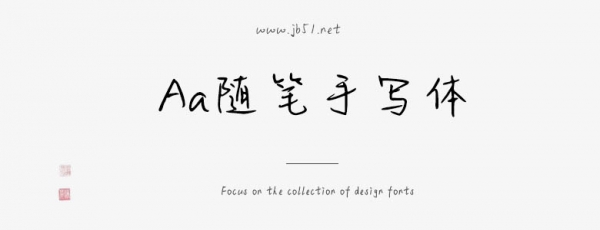
Aa隨筆手寫(xiě)體是一款不錯(cuò)的藝術(shù)字體,由Aa字庫(kù)出品,字體筆觸略細(xì),書(shū)寫(xiě)流暢,擁有字符數(shù)8040和字形數(shù)8008,具有很好的視覺(jué)感,適合應(yīng)用于藝術(shù)設(shè)計(jì)、平面宣傳設(shè)計(jì)、網(wǎng)頁(yè)設(shè)計(jì),書(shū)法字帖等領(lǐng)域,需要的朋友可以前來(lái)本站下載。